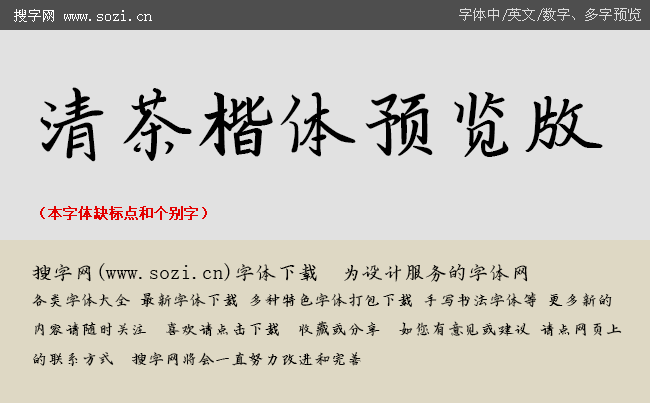
清茶楷體預(yù)覽版
搜字網(wǎng)提供一款清茶楷體預(yù)覽版下載,清茶楷體字體細(xì)致柔順,瘦小的筆觸卻給人剛毅有力的感覺,又不失清秀。是一款非常好看的的字體文件。適合畫冊正文、報(bào)紙排版、展版設(shè)計(jì)、海報(bào)設(shè)計(jì)等廣告設(shè)計(jì)場合使用。